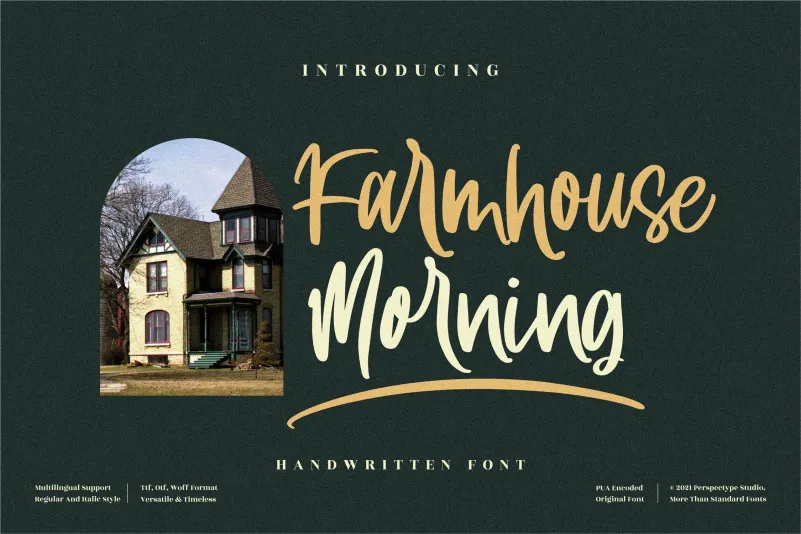
Esta é uma fonte escrita a mão, leve e amigável, perfeita para criar ambientes confortáveis e descontraídos. Seja ela para assinaturas, títulos de livros ou até mesmo as descrições do seu blog, a Farmhouse Morning font tem o potencial de tornar qualquer projeto mais sofisticado e interessante. Seu estilo relaxado e amigável faz dela uma excelente adição à sua biblioteca de fontes, especialmente para ambientes rústicos e acolhedores. Perfecta tanto para nomes de lojas como para textos informativos em blogs ou websites, esta fonte se adequará perfeitamente a qualquer projeto que desej você ofereça conforto visual e harmonia à sua proposta. Criada pelo designer perspectype, essa fonte é uma opção ideal para aqueles buscando personalidade e sutileza em seus materiais digitais. Seja ela usada em uma página de blog sobre cozinha, ou como título na capa de um livro de receitas, a Farmhouse Morning font irá destacar sua proposta criativa e encantadora. Além disso, sua leveza mantém o foco no conteúdo que você deseja transmitir, oferecendo um toque especial ao seu trabalho visual.